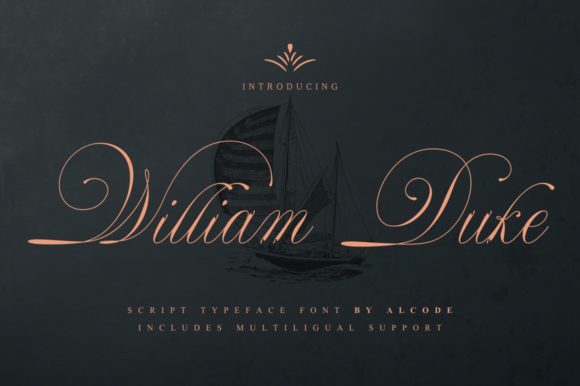
William Duke - это роскошный и восхитительный сценарий с великолепными мотивами.
Этот классический каллиграфический шрифт выделит любой дизайн-проект.